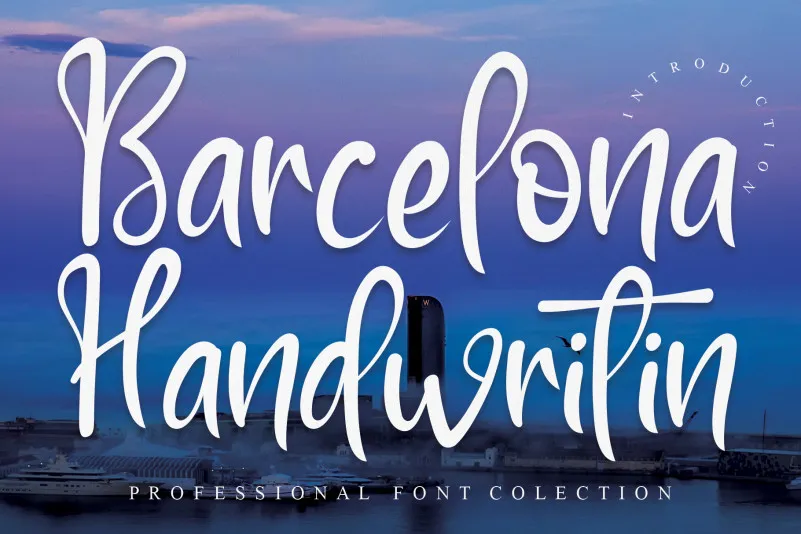
A Barcelona Handwritin Font é uma fonte manual cínica e descontraída, perfeitamente adaptada para agregar vida à sua identidade visual. Ideal tanto para designers quanto para pessoas que apreciam elementos modernos e alegres na produção de materiais gráficos, esta fonte se destaca por seu charme natural e seu toque leve. Seja em cartazes, letrinhas do site ou até mesmo em trabalhos de marketing digital, ela é uma escolha perfeita para aqueles que buscam uma cor das cores vivas da cidade de Barcelona no formato do qual mais gostam: a escrita manual. Como uma fonte criada pelo designer andikastudio, a Barcelona Handwritin Font oferece um toque moderno que enriquece os designers em qualquer projeto gráfico, tornando cada obra sua própria peça única e especial.